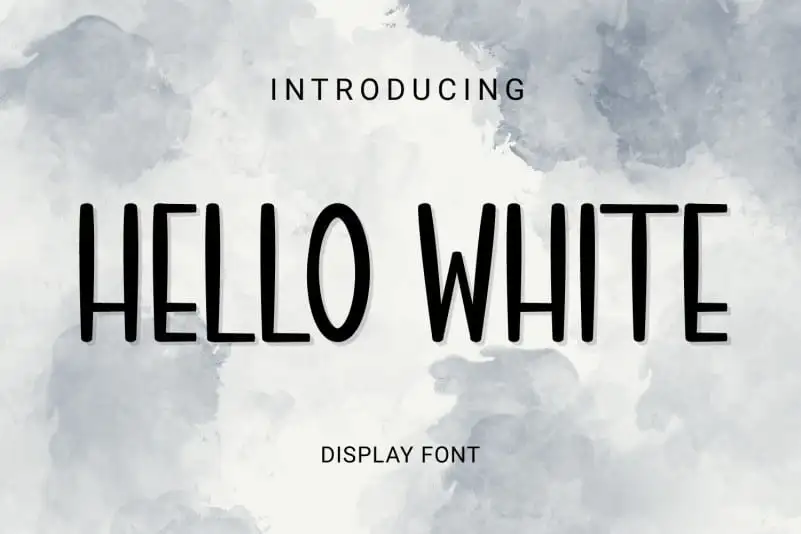
Hello white Display Font – Fonte Grátis
Hello white Display Font
A fonte “Hello white Display Font” é uma escolha perfeita para quem busca criatividade num estilo simples e limpo. Sua disposição levemente desenhada faz com que seu texto destaque-se de forma atraente, tornando seus projetos mais chamativos. Este elegante display font não apenas adiciona um toque diferente aos seus trabalhos gráficos, mas também eleva-os acima do resto da maioria dos outros recursos disponíveis. Ideal para uso em design editorial e publicidade, o Hello white Display Font é a solução perfeita se você está à procura de algo mais que a convenção. Com seu designer talentoso Planetz Studio, estamos felizes por poder apresentá-lo como uma fonte versátil e eficaz no seu arsenal gráfico.